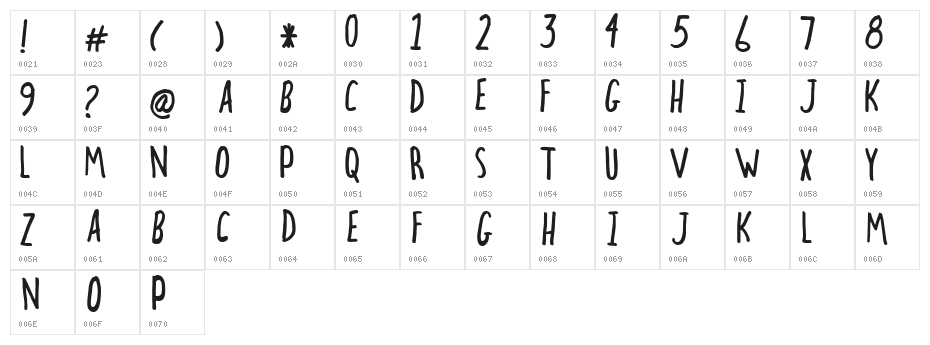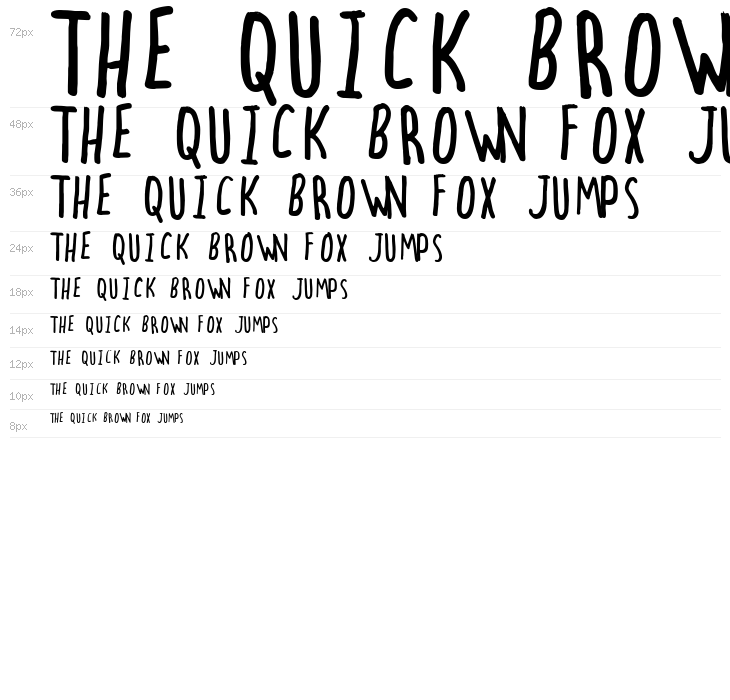
hectic Font
✎ Capitals
| Gesamtstil | Casual |
| Anwendungsfall | Headlines, Logos, Informal Text |
| Vorgeschlagene Projekte | Ideal for greeting cards, children's books, casual branding, and social media graphics. |